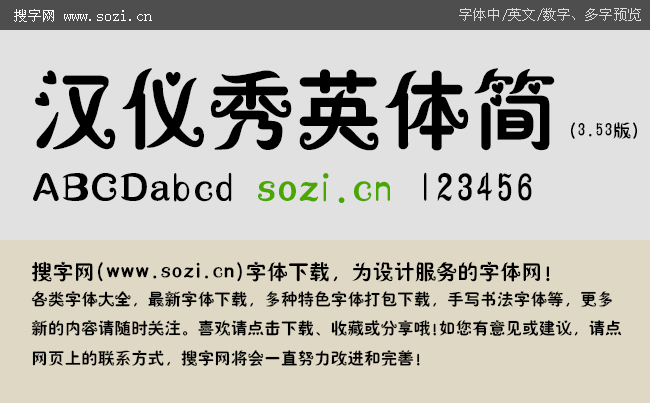
漢儀秀英體簡(jiǎn)
搜字網(wǎng)給大家提供一款漢儀秀英體簡(jiǎn)體卡通中文字體下載。漢儀秀英體橫豎筆畫粗細(xì)基本相同,橫平豎直,筆畫兩頭是圓形,點(diǎn)是雞心形桃點(diǎn),撇為飄動(dòng)的柳葉形,捺向右方飛起,是一款非?蓯鄣拿佬g(shù)字體。適合海報(bào)設(shè)計(jì)、廣告標(biāo)題的應(yīng)用。